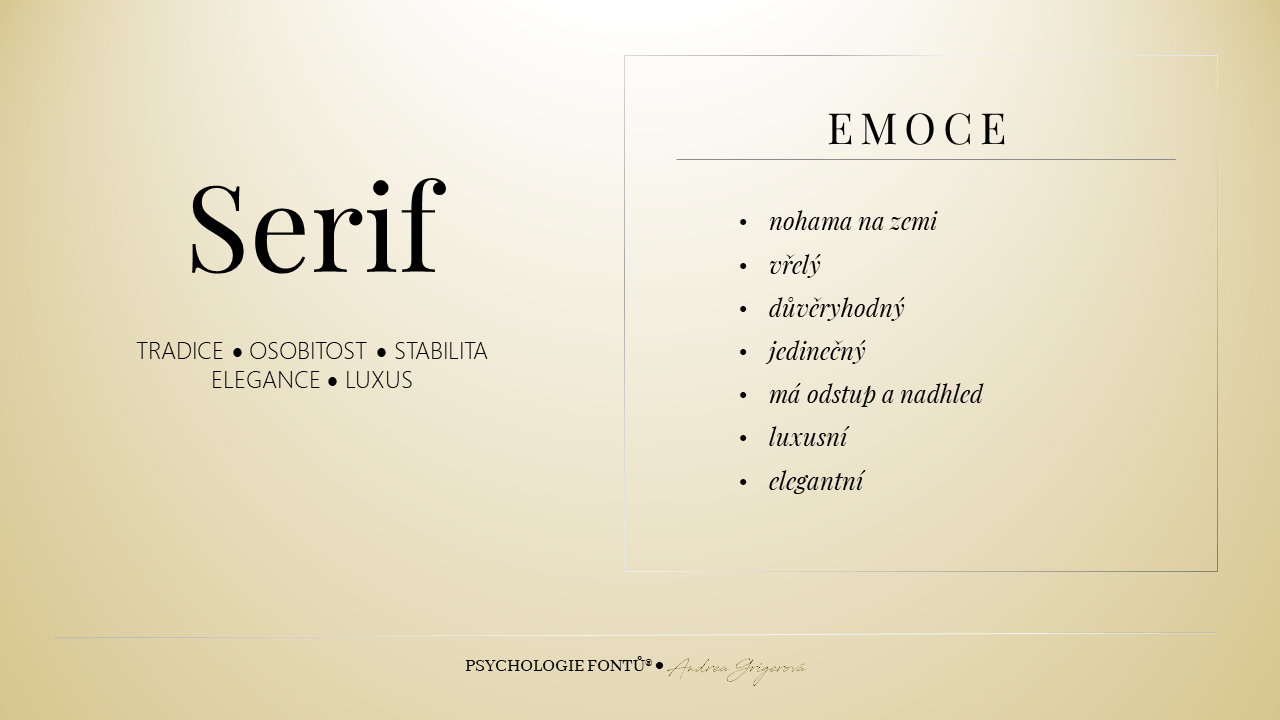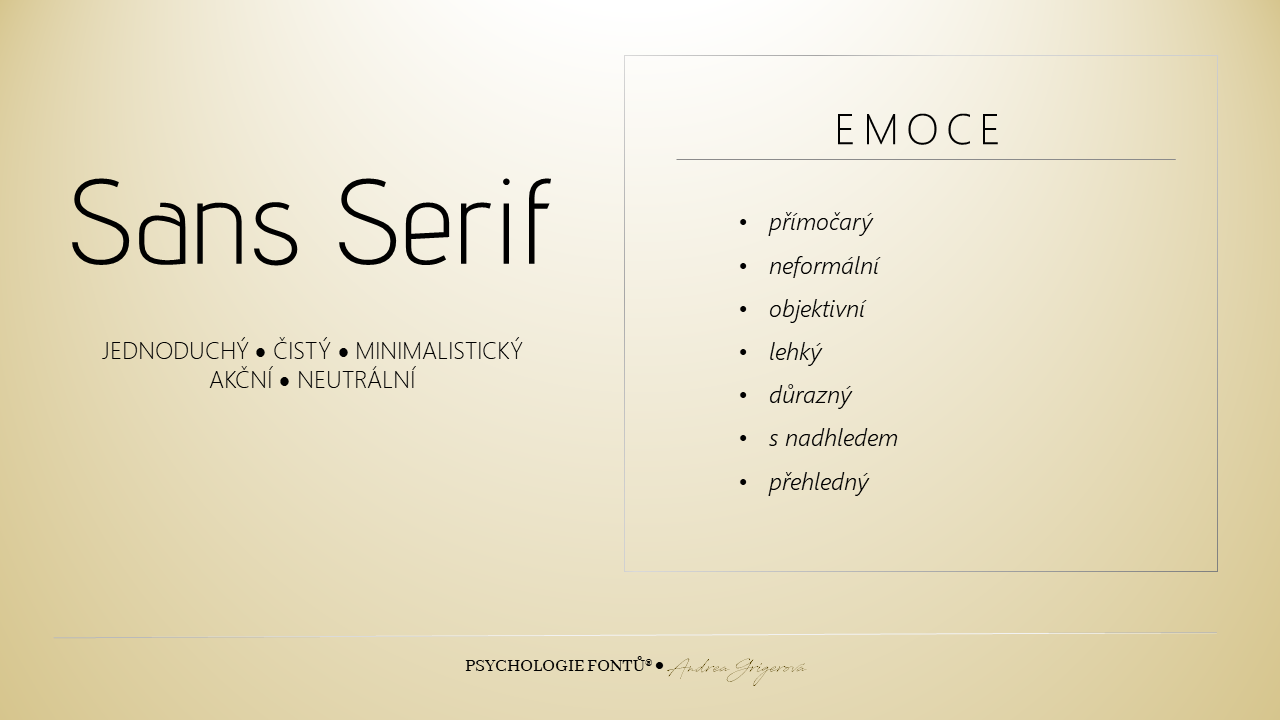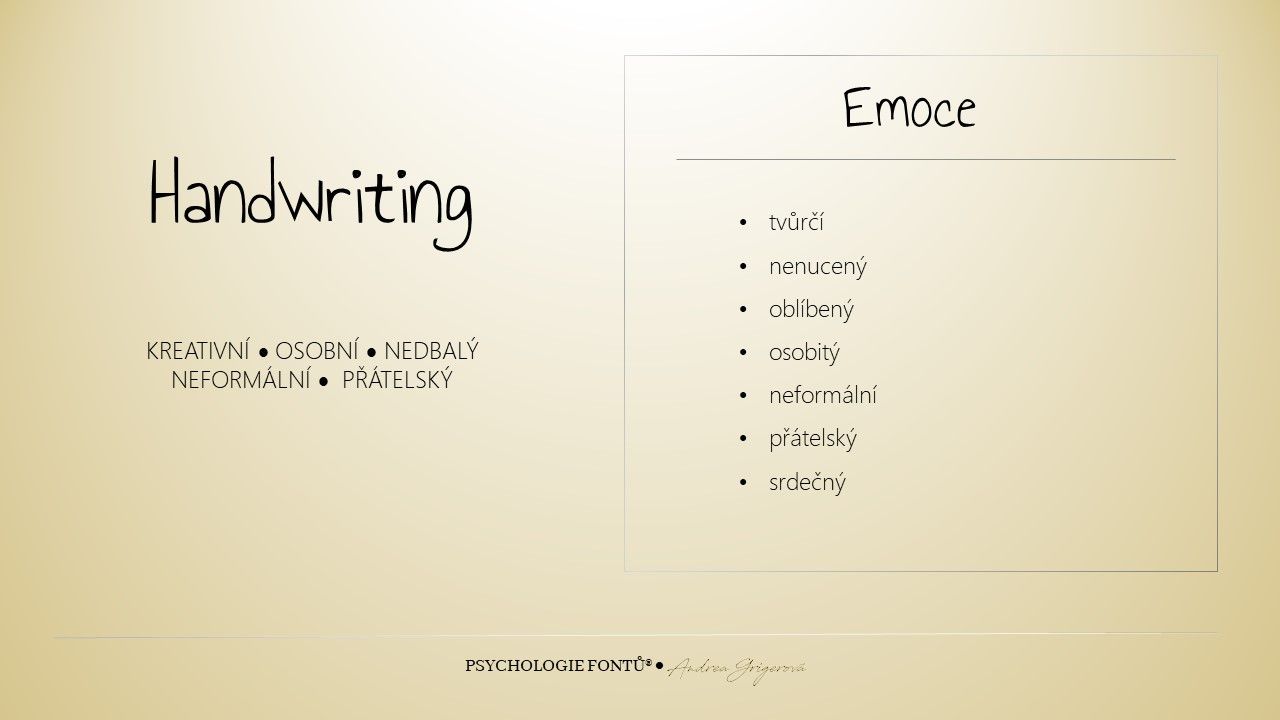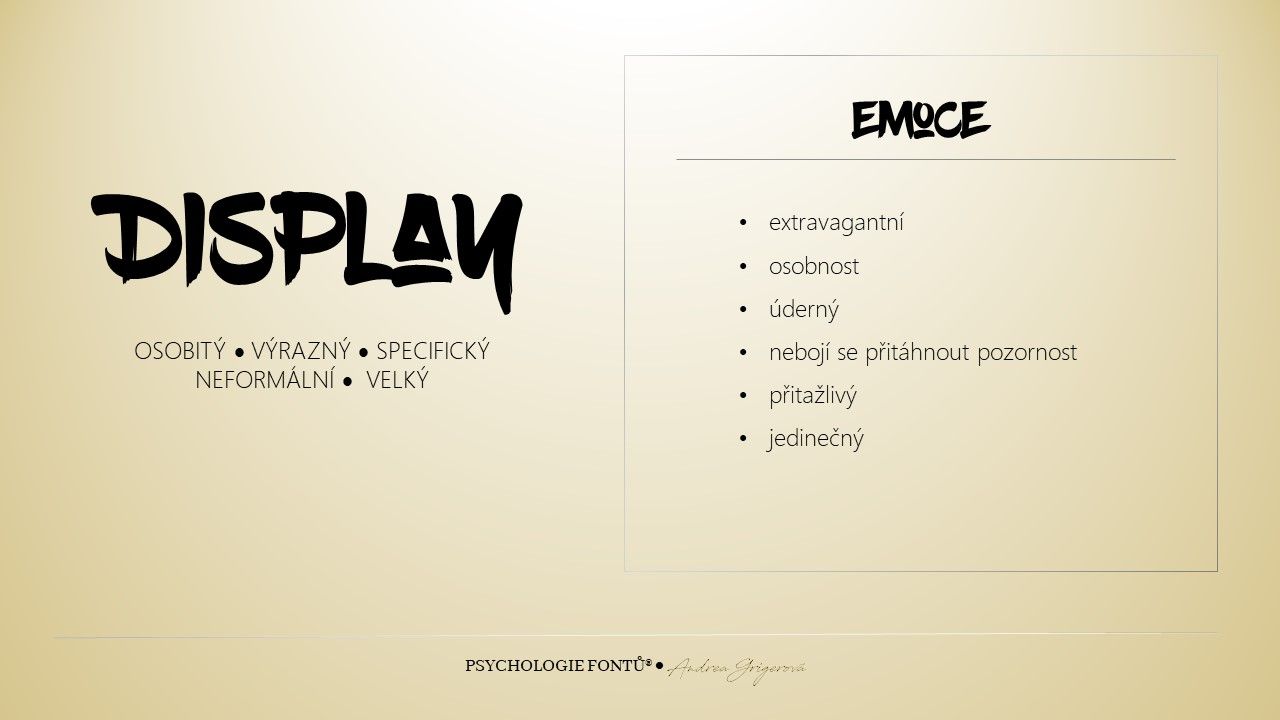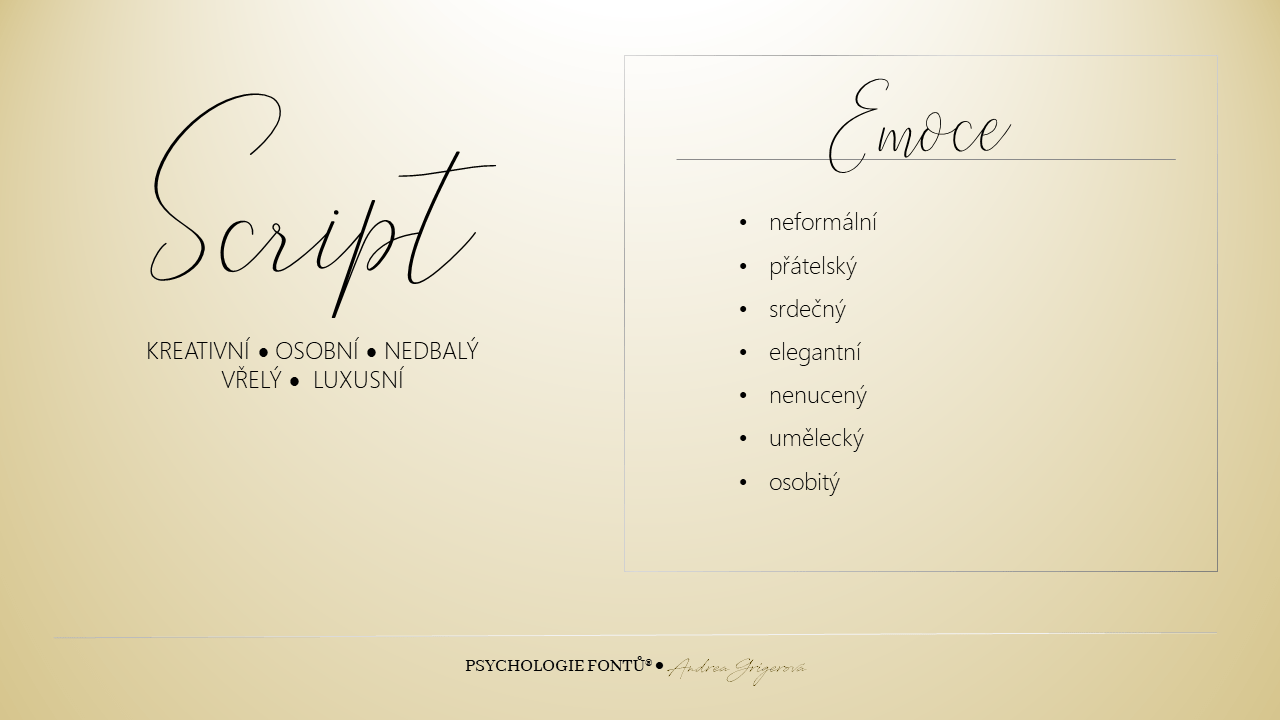
Hledáte font a netušíte, jestli vybrat patkový, bezpatkový nebo ručně psaný? A vůbec, co jsou to ty patky? A jak se v tak obrovském množství fontů orientovat?
Nezoufejte, systém existuje. Fonty můžeme rozdělit do různých skupin, například patkové a bezpatkové, proporcionální a neproporcionální, antikvové a kurzívní nebo volně kreslená a script. Ale abyste se v tom neztratili, začneme jednoduše těmi nejvýraznějšími zástupci.
Pokud víte, ze které skupiny chcete vybírat, máte skoro vyhráno. Potřebujete ale vědět, co jsou jednotlivé skupiny fontů zač, co vám která nabízí a na co je vhodná. Výběrem toho správného fontu totiž dosáhnete nejenom toho, že se text bude skvěle číst, ale hlavně toho, že vzbudíte ve čtenáři emoce, které chcete vzbudit. A pokud vybíráte font pro váš web nebo značku, dejte si hodně záležet.
Pojďme se na jednotlivé zástupce podívat zblízka.
Patkový font
Jsem důvěryhodný. To o sobě slyším nejčastěji.  A stojím nohama na zemi. Nelétám ve vzduchu, nevznáším se na křídlech snů a inspirace. Pravda, chybí mi lehkost, ale zato vás skvěle uzemním. Potřebujete věřit? Ukázat, že nevaříte z vody a stavíte na pevných základech? Potřebujete se ponořit do hloubky a nebaví vás tlachat o počasí? Tak to vám zprostředkuju právě já. Beru na sebe různé podoby, dokážu být mile starosvětský Im Feel English, odtažitý Slabo 27px nebo elegantní Georgia. Ale vždy mám dvě esence, které těžko hledáte jinde. Hloubka a důvěra.
Patky patřily k písmu odjakživa, vznikly jako přirozené zakončení tahu, při nasazení dláta (kamen) nebo brka (pergamen). Jejich tvar se v průběhu staletí měnil, stejně tak jako nástroje, kterými se psalo a materiál, na který se psalo. Patky mají velký vliv na to, jak písmo vnímáme, jak na nás působí. Nejenom jejich tvar, ale i nasazení na tah písma.
Bezpatkový font
Mám nadhled. Dokážu vám nabídnout lehkost a přehlednost. Jsem často povrchní, protože chci předat informace rychle a bez zbytečných cirátů. Nechcete se v něčem šťourat a přemýšlet nad nesmrtelností chrousta? Potřebujete bezproblémovou a rychlou komunikaci s druhými? To je moje parketa. Také mám různé nálady a podoby. Jsem přátelský a rád komunikuji (Centhury Gothic), občas jsem se vším rychle hotový (Open  sans Condensed), ale dokážu být i jemná a citlivá duše (Alegreya Sans). Milují mne výkonní a racionální lidé, kteří nechtějí ztrácet čas hloupostmi.
Bezpatkový font zažívá boom s érou monitorů a displejů. Vznikl už někdy v 19. století postupným zjednodušováním konců tahů patkových písmen, ale až 20. století mu přeje naplno. Ke zvýraznění či podnadpisu můžete použít různé jejich řezy (kurzíva, tučný řez,…). I mezi nimi se ale najdou výtečníci, kteří spadají do skupiny nadpisových fontů a ty vyniknou (a jsou dobře čitelné) pouze ve větších velikostech písma.
[box background=#e8e8e8]Patkové i bezpatkové fonty jsou univerzální, můžete je používat v dlouhých odstavcích, v nadpisech i poznámkách. [/box]
Ručně psaný font
Jsem cíťa. Dávám najevo emoce, city a pocity daleko lépe než všichni patkoví a bezpatkoví kamarádi dohromady. A také je dokážu vzbudit. Potřebujete osobní komunikaci a nebojíte se ukázat pocity? Chcete zapojit do textu pravou hemisféru a zacílit ho přesně na vaše čtenáře? V tom jsem jedinečný. Dokážu naladit čtenáře na tu pravou strunu tak, aby se v textu našel. Aby vzbudil úsměv na tváři, pobavil, prostě nebyl takový studený čumák jako je třeba bezpatkový font. A tolik výrazů jako já nemá nikdo. Jsem žensky romantický (Great Vibes), chlapsky nedbalý (Desyrel), unisex přátelský (Kalam) i kreativní duše (Brusher).
[box background=#e8e8e8]S ručně psaným fontem šetřte jako se šafránem.[/box]
V delších větách je špatně čitelný a v odstavcích je se stává nečitelným. Je to jako s emocemi, když je druhému ukážete, tak potěší, ale když jich na druhého vychrlíte příliš, uteče. Na anglických webech se tato skupina často dělí na SCRIPT a HANDWRITING.
Nadpisový font
Miluju pozornost. A také udělám vše proto, abych jí na sebe strhnul. Já udávám tón celého článku a dokážu se pořádně rozšoupnout. Pokud hledáte parťáka pro nadpisy na webu, filmovém plakátu, v knize nebo v článku, rád vám pomůžu. Vyniknu daleko lépe než patkoví a bezpatkoví kolegové a nejsem taková cíťa jako ručně psané kámošky. A vezmu na sebe podobu, jakou potřebujete. Chcete drsňáka (Arial Black), intelektuála (Mager), divného chlápka (Albersthal Typewriter) nebo hvězdu (Broadway)? Stačí si vybrat.
[box background=#e8e8e8]Nadpisový font vynikne pouze při větší velikosti písma.[/box]
Pokud ho zvolíte jako font normálního textu v odstavci, bude buď špatně čitelný, divný nebo takový nijaký. Je prostě proporčně stavěný na nadpisy a ne na blechy. Naopak patkové a bezpatkové fonty nestačí zvětšit na velkost nadpisu, aby se z nich staly nadpisové a měly stejný dopad. Důvod? Stejný. Nadpisové fonty mají jiné proporce.
Poznali jste 4 základní skupiny fontů. Až příště budete váhat, jaký font vybrat, zkuste se předem zamyslet, k čemu má text sloužit. Má neverbálně předávat vaší profesionalitu a důvěryhodnost? Má přitáhnout pozornost a pobavit? Nebo přitáhnout pouze čtenářky k citlivému ženskému tématu? Váš výběr fontů bude poté jednodušší a hlavně, uvědomíte si, co chcete článkem či webem dosáhnout.